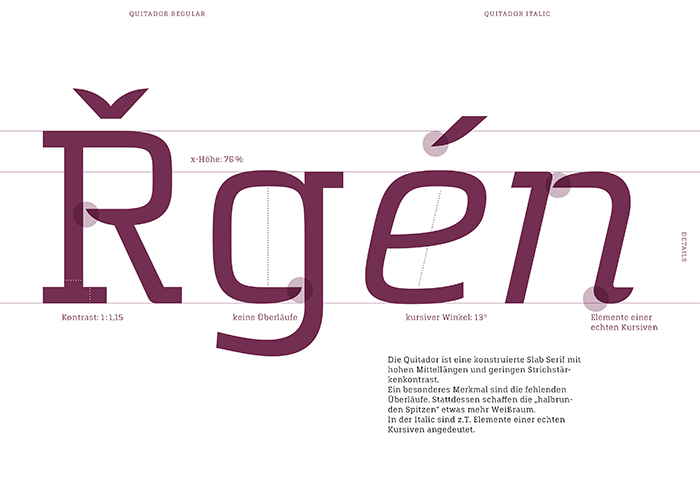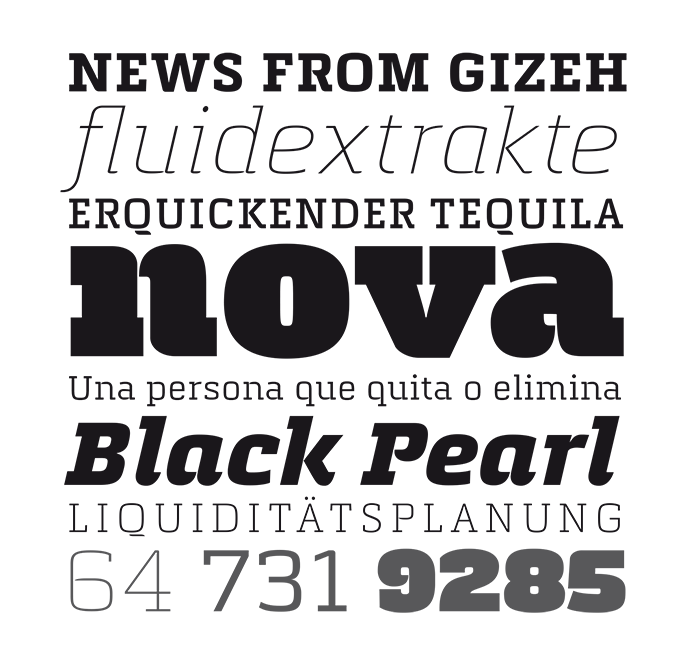
Die Quitador ist eine Slab-Serif-Schrift von Arne Freytag. Die Schrift ist bis auf die teilweise abgerundeten Strichenden monolinear ausgeführt und besitzt sieben Strichstärken mit Kursiven.